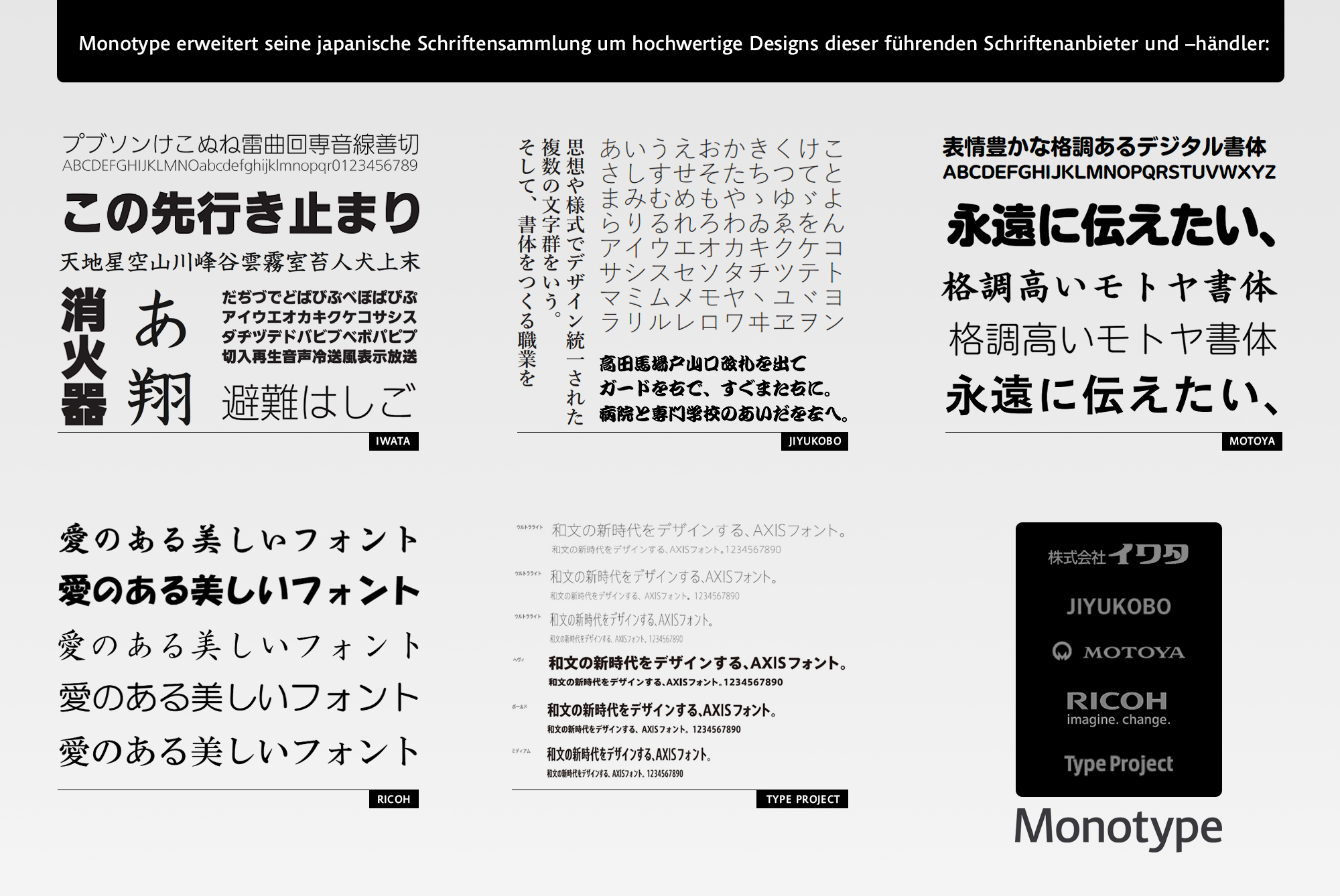
Monotype baut japanisches Font-Angebot aus: Über 500 hochwertige Schriften führender japanischer Anbieter
Viele der neuen Schriften erstmals außerhalb Japans verfügbar
Über 500 hochwertige Schriften führender japanischer Anbieter bei Monotype(firmenpresse) - Bad Homburg, 22. Oktober 2013 - Die Monotype GmbH, ein führender Anbieter von Schriften, Technologie und Expertise für kreative Anwendungen und Consumer-Geräte, kooperiert mit mehreren der bedeutendsten japanischen Schriftenanbietern und -händlern, um das Monotype-Angebot an hochwertigen japanischen Fonts zu erweitern. Die neuesten Schriften umfassen Designs von Iwata, JiyuKobo, Motoya, Ricoh und Type Project. Damit können nun insgesamt mehr als 500 hochwertige japanische Schriften für eine Reihe von Anwendungsmöglichkeiten bei Monotype lizenziert werden.
Die Monotype-Auswahl japanischer Schriften ist derzeit eine der umfangreichsten der Welt. Die neuesten Ergänzungen, die zum Teil erstmals außerhalb Japans verfügbar sind, werden über die direkten Verkaufskanäle von Monotype sowie die Webseiten Fonts.com und Linotype.com lizenziert. Zusätzlich zu Lizenzen für Webfonts und traditionelle Desktop-Fonts bestehen Lizenzierungsmöglichkeiten für mobile Anwendungen, E-Publikationen und webbasierte Services sowie für OEMs und Entwickler von Consumer-Geräten.
"Durch diese erstklassigen Anbieter konnten wir die Auswahl und Bandbreite an sofort verfügbaren und hochwertigen japanischen Schriften entscheidend ausbauen", sagt John Seguin, Executive Vice President bei Monotype. "Dies ist ein echter Gewinn für unsere Kunden auf der ganzen Welt, insbesondere für diejenigen, die Inhalte in der Markenkommunikation schaffen und verbreiten oder Produkte entwickeln, die mehrere Sprachen unterstützen. Unser Anspruch ist es, unseren Kunden Markentreue zu ermöglichen und den immer globaler werdenden Ansprüchen an die Typographie gerecht zu werden."
"Für internationale Marken sind japanische Schriften extrem wichtig, um ein glaubwürdiges Auftreten in lokalen Märkten zu erreichen", sagt Alex de Jánosi, Partner beim globalen Markenstrategie und -design-Berater Lippincott. "Das ist die Antwort auf eine der entscheidendsten Fragen bei Design und Produktion: Der Zugang zu hochwertigen, zuverlässigen mehrsprachigen Fonts."
Die japanische Kollektion von Monotype bietet eine große Bandbreite von Stilen, darunter klassische Mincho- und Gothic-Designs in verschiedenen Strichstärken sowie Pinsel- und Deko-Stile. Die Schriften wurden für optimale Leserlich- und Lesbarkeit sowohl auf dem Bildschirm als auch für Print-Material entwickelt und ergänzen koreanische, chinesische und weitere Schriften aus dem Monotype-Angebot. Zusätzlich sind einige der Fonts von den Monotype-Schriftenpartnern als Universal Design (DU) ausgelegt: Sie verfügen über vereinfachte Formen und weitere Details für eine möglichst klare Darstellung auf elektronischen Displays.
Die neuesten Erweiterungen des japanischen Schriftangebots von Monotype umfassen Schriften folgender Anbieter:
Iwata Corp.
1920 gegründet, ist die Iwata Corp. einer der ältesten und renommiertesten Schriftenanbieter Japans und verfügt über eines der größten Angebote an hochwertigen japanischen Fonts für digitale und gedruckte Anwendungen. Die Iwata-Schriftenbibliothek umfasst viele beliebte Schriftdesigns und ist für exzellente Lesbarkeit, Tradition und Detailtreue bekannt. 2009 erhielt Iwata den Good Design Award für seine Universal Design Fonts, d.h. Designs, die gezielt für die Verwendung für User-Interfaces und sonstige Bildschirmanwendungen optimiert wurden.
JiyuKobo Ltd.
JiyuKobo ist ein führender japanischer Schriftenanbieter und wurde 1989 gegründet. Die Schriftdesigner und -entwickler des Hauses haben zahlreiche Mincho- und Gothic-Schriften mit markanten Eigenschaften sowie traditionelle Stile für die Verwendung im Digital- und Printbereich gestaltet. JiyuKobo gewann 2008 den Type Directors Club Tokyo Price sowie den Good Design Award.
Motoya Co. LTd.
Gegründet im Jahr 1922, verfügt Motoya über eine lange Geschichte in der Schriftentwicklung, die vom Blei- und Fotosatz bis zur digitalen Schriftverwendung auf dem Bildschirm reicht. Die Motoya-Schriftenbibliothek umfasst ein vielfältiges Angebot an Schriftstilen für den Digital- und Printbereich. Die Motoya-Designs sind darüber hinaus für ihre Schönheit und hervorragende Lesbarkeit bekannt.
Ricoh
1936 gegründet ist Ricoh ein globales Technologieunternehmen, das auf Bildgebungstechnologien im Office-Bereich, Produktionsdrucklösungen, Dokumentenmanagement-Systeme und IT-Services spezialisiert ist. Die japanische Font-Sammlung von Ricoh umfasst ein vielfältiges Schriftenset, darunter die berühmten HG Mincho und HG Gothic-Fonts. Neben den bisher im Monotype-Angebot enthaltenen Ricoh-Schriften und Embedded Services können die Fonts jetzt auch für Desktop, Web, Mobile Apps, E-Publikationen und Web-enabled Services lizenziert werden.